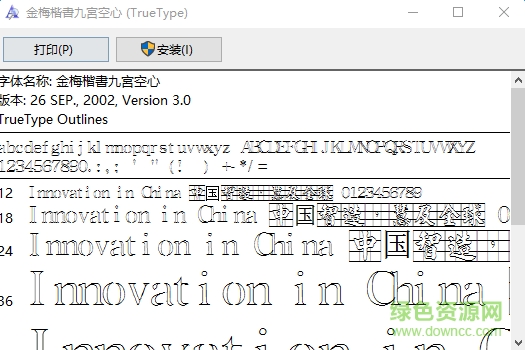
金梅楷書九宮空心
金梅楷書九宮空心字體是金梅字庫楷書字體中的一款空心字體,說到這個詞有沒有覺得很時尚呢,字體是空心的,相比寫出來的字也會很好看的,大家可以來綠色資源網(wǎng)下載試試看哦。
金梅楷書九宮空心字體這款字體寫出來的字很好看,而且很有特色,用于藝術(shù)設(shè)計(jì)、廣告設(shè)計(jì)都是很不錯的,歡迎大家來綠色資源網(wǎng)下載。